Die coolsten Schriftarten für Gamer-Namen
Dominiere in CS2, LoL und Fortnite. Mach deinen Gamer Namen Schrift zur Marke – ohne Installation, 100% kostenlos.
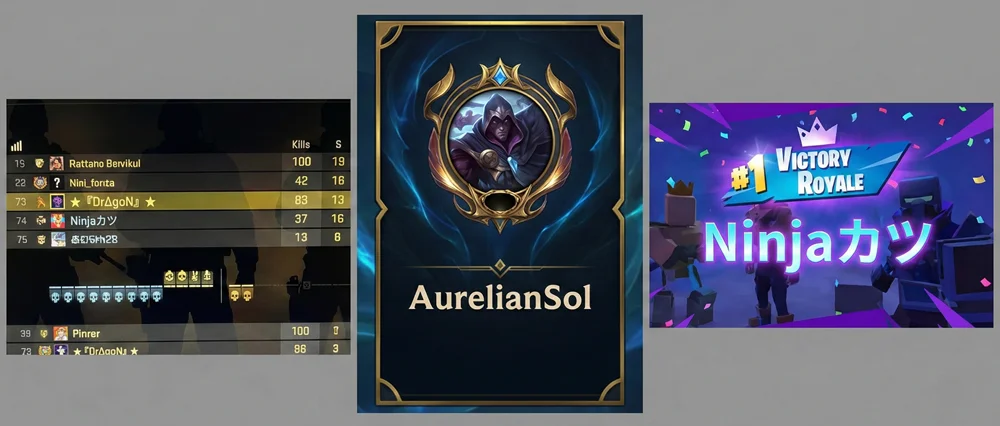
Du betrittst die Lobby, und dein Name sieht genauso aus wie der von Millionen anderen Spielern: Standard-Schriftart, langweilig, unscheinbar. Willst du das wirklich? Oder willst du, dass dein Nickname schon im Ladebildschirm Angst und Respekt einflößt?
In der Gaming-Welt ist dein Name deine Marke. Egal, ob du in Counter-Strike 2 (CS2) Headshots verteilst, in League of Legends (LoL) die Lane dominierst oder in Fortnite den Victory Royale holst – dein Name muss auffallen.
Warum eine besondere Gamer Schriftart wichtig ist
Es geht um mehr als nur Ästhetik. Es geht um Identität. Pro-Gamer und erfolgreiche Streamer nutzen fast immer spezielle Zeichen oder Schriftarten, um sich von der Masse (den “Noobs”) abzuheben.
- ✓Wiedererkennungswert: Dein Clan oder deine Freunde finden dich sofort auf dem Scoreboard.
- ✓Einschüchterung: Ein Name wie
꧁༒Sniper༒꧂wirkt deutlich gefährlicher alsSniper123. - ✓Individualität: Zeige deinen persönlichen Style, sei es Gothic, Cyberpunk oder minimalistisch.
Der ultimative Guide für deine Lieblingsspiele
Nicht jede Gamer Namen Schrift passt zu jedem Spiel. Hier ist, worauf du achten musst:
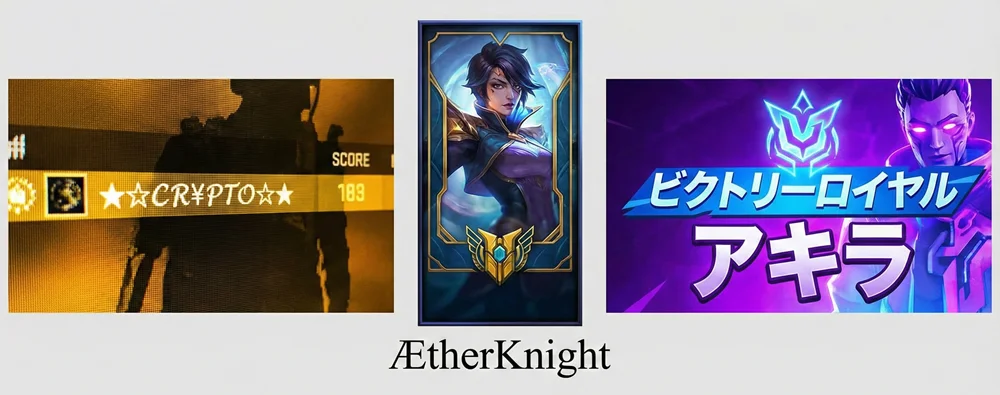
1. Counter-Strike 2 (CS2) & Steam
In CS2 läuft alles über deinen Steam-Namen. Steam ist sehr tolerant, was Unicode-Zeichen angeht.
Standard: TheKiller
Pro: 𝖳𝗁𝖾𝖪𝗂𝗅𝗅𝖾𝗋
Tipp: Nutze “Wide Text” für mehr Platz im Kill-Feed.
2. League of Legends (LoL)
Riot Games ist strenger. Manche Zeichen werden als Kästchen angezeigt.
Tipp: Nutze “Small Caps” oder “Serif”-Styles. Diese sehen im Ladebildschirm extrem “clean” aus.
3. Fortnite (Epic Games)
Beliebt sind “Sweaty Usernames” mit kurzen Namen und Symbolen.
Beispiel: Ryze ツ
Tipp: Kombiniere Schrift mit Symbolen wie Smileys oder Kanji.
Wie funktioniert der Schriftgenerator?
Unser Tool nutzt einen cleveren Trick namens Unicode. Unser Generator wandelt deinen normalen Text nicht in eine “neue Schriftart” um, sondern ersetzt deine Buchstaben durch Unicode-Symbole, die einfach nur so aussehen wie ausgefallene Buchstaben.
Auswählen: Unser Tool generiert sofort Dutzende Varianten (Gothic, Double-Struck, Circles).
Häufig gestellte Fragen (FAQ)
Warum werden manche Zeichen als Kästchen (☐) angezeigt?
Wenn du nur Kästchen siehst, bedeutet das, dass das Spiel oder das Gerät des anderen Spielers dieses spezifische Unicode-Zeichen nicht “lesen” kann. Probiere in diesem Fall einen “cleaneren” Style aus unserem Generator.